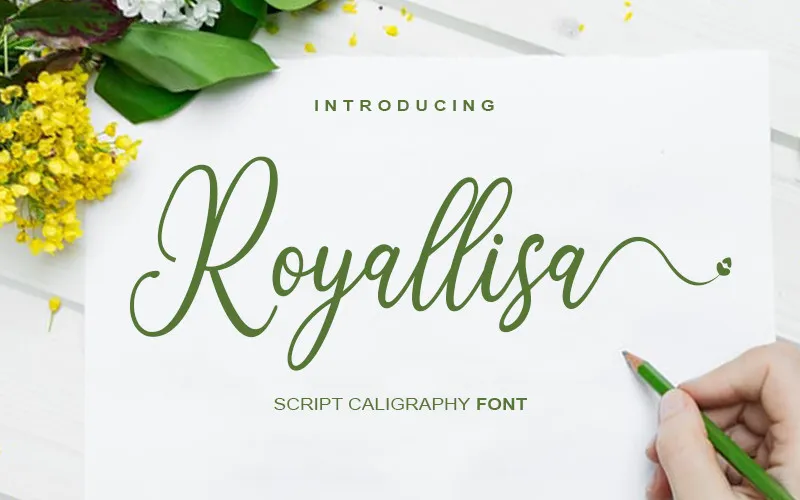
Royallisa Font – Download Grátis
Royallisa é uma linda fonte escrita à mão que se destaca pelo seu estilo clássico incrivelmente elegante, mantendo ao mesmo tempo um toque amigável e leve. Essa fonte perfeita para designers quer fazer trabalhos originais e excepcionais. Seja você designer de cartazes ou editor gráfico, Royallisa trará uma nota especial a cada projeto. Inspirado pelo espírito delicado da escrita à mão, este design inovador é o tipo certo para criar designs memoráveis sem perder a elegância e personalidade exclusivas. Quebre as regras de estilo e seja criativo com Royallisa; ela irá adicionar um toque único ao seu trabalho.